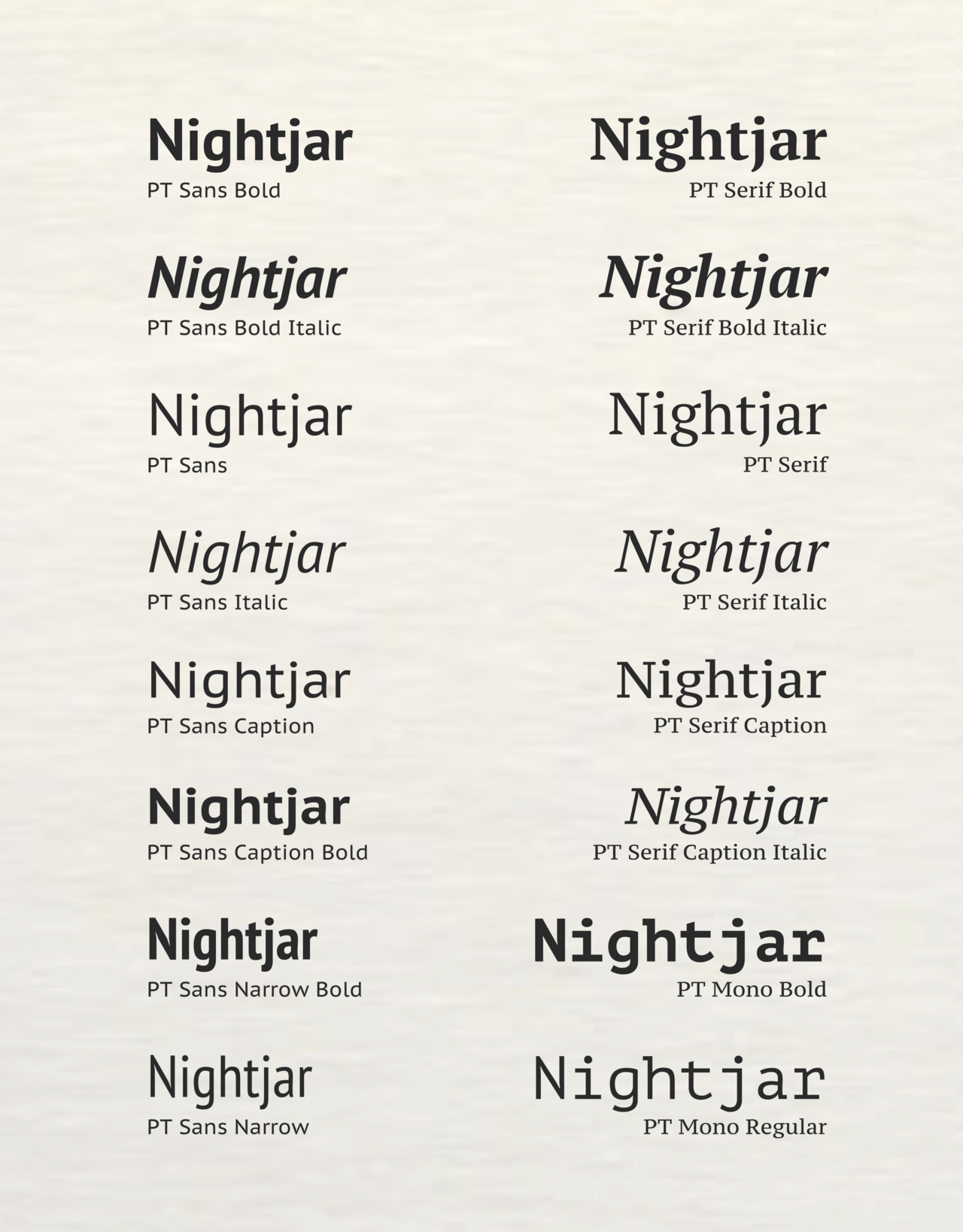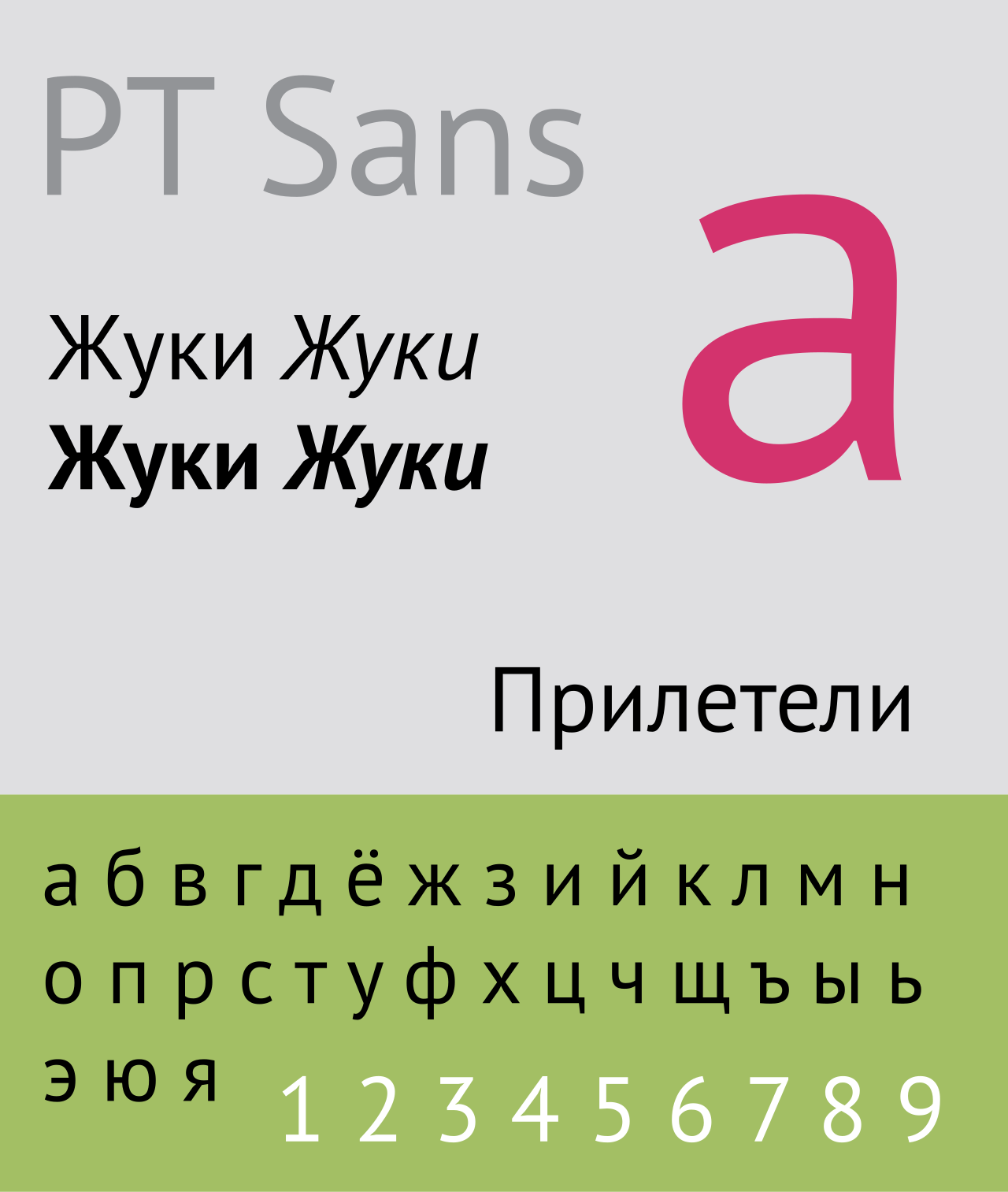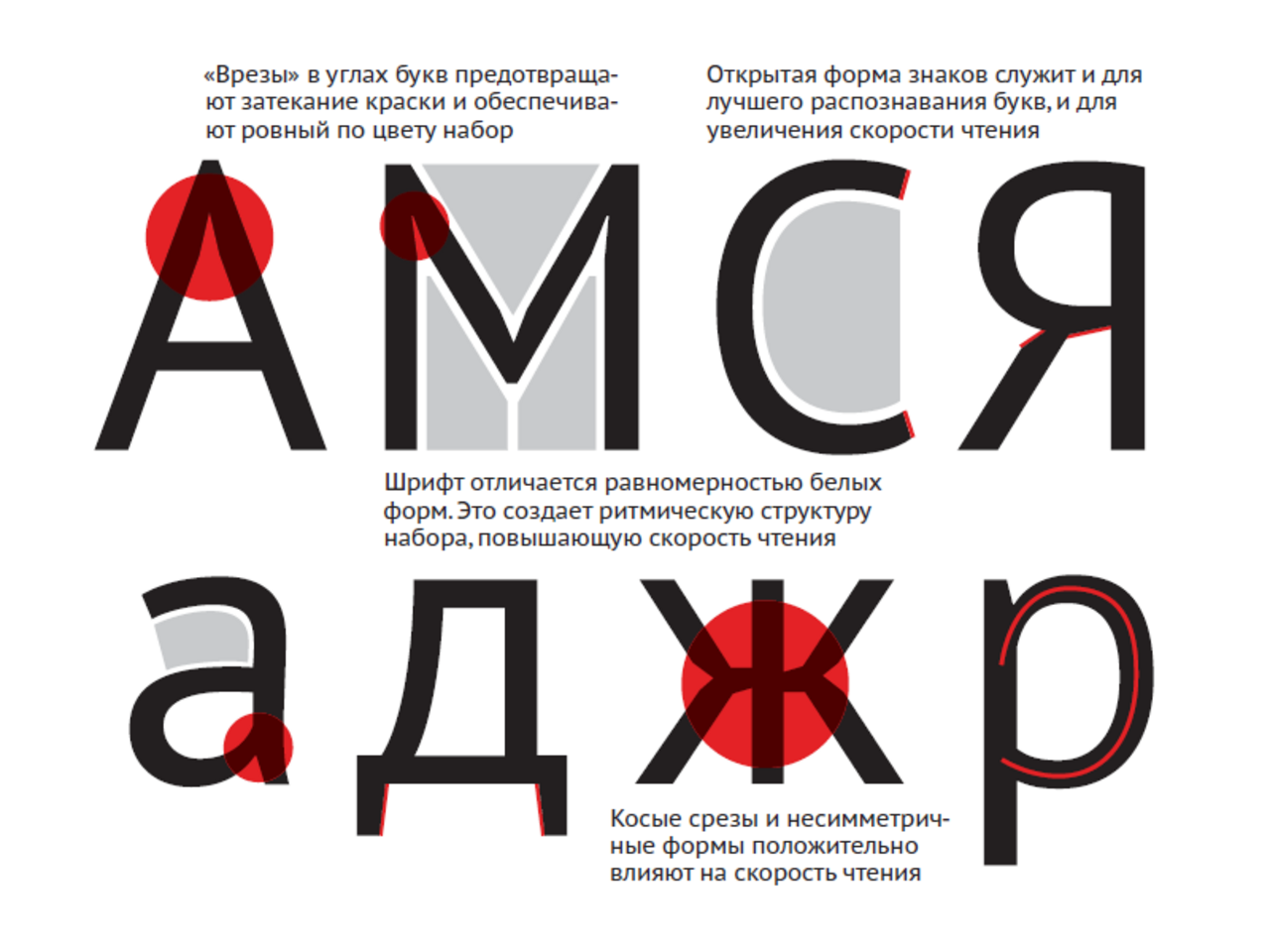
خطوط PT
| تصنيف | خط إنساني بلا رقيق انتقالي أحادي المسافة |
| المصمم(ون) | ألكسندرا كورولكوفا مع أولغا أومبيلوفا وفلاديمير يفيموف |
| بتكليف من | روزبشات |
| مسبك | النوع الفرعي |
| تاريخ الإنشاء | 2009 |
| تاريخ الإصدار | 13 يناير 2010 [1] |
خطوط Public Type أو PT هي عائلة من الخطوط المجانية والمفتوحة المصدر التي تم إصدارها منذ عام 2009 فصاعدًا، وتضم PT Sans و PT Serif و PT Mono . وقد تم تكليف وكالة التصميم ParaType بواسطة Rospechat ، وهي إدارة تابعة لوزارة الاتصالات الروسية ، بتصميم هذه الخطوط للاحتفال بالذكرى السنوية الـ 300 لإصلاح الإملاء الذي قام به بطرس الأكبر وإنشاء عائلة خطوط تدعم جميع الاختلافات المختلفة للنص السيريلي المستخدم من قبل اللغات الأقلية في روسيا ، بالإضافة إلى الأبجدية اللاتينية . [1] [2]
تم تصميم هذه العائلة في الأساس بواسطة ألكسندرا كورولكوفا ، وتتضمن تصميمات بدون تذييلات وتذييلات ، وكلاهما مع أنماط تعليق للنصوص المطبوعة بحروف صغيرة، وخط أحادي المسافة للاستخدام في البرمجة. وهي متوفرة بموجب ترخيص SIL Open Font باللغة الإنجليزية ؛ تم إصدار الخط الأصلي، PT Sans ، أيضًا بموجب ترخيص الخطوط المجاني الخاص بشركة ParaType، والخط العادي والغامق مع الخط المائل مجاني في Google. [3] يتم بيع أنماط إضافية، مثل الموسع والمكثف والغامق للغاية، من ParaType باسم PT Sans Pro وPT Serif Pro. [4] [5]
سمات
تتضمن الخطوط حروفًا لاتينية وسيريلية وتغطي جميع اللغات الأقلوية تقريبًا في الاتحاد الروسي. تم تضمين رمز الروبل المائل Р (قبل أن يصبح رسميًا في ديسمبر 2013) في نقاط الرمز U+20B9…U+20CF.
في أكثر إصدارات المصادر المفتوحة شيوعًا، يتميز PT Sans وPT Serif بتصميمات عادية ومائلة وغامقة ومائلة غامقة. كما يتضمنان نمط تسمية توضيحية : وهو إصدار أوسع من الخط مع ارتفاع x أكبر (أحرف صغيرة أطول)، مصمم لسهولة القراءة بأحجام الخطوط الصغيرة وعلى اللافتات الخارجية. يتضمن PT Sans أيضًا إصدارًا مكثفًا بالخط العادي والغامق بدون مائل. في أنماط التسمية التوضيحية، يحتوي PT Serif على نمط تسمية توضيحية مائلة بينما يحتوي PT Sans على إصدار غامق. يتضمن PT Mono أنماطًا عادية وغامقة.
تتضمن الإصدارات التجارية لخط PT Sans أوزانًا إضافية خفيفة وشبه غامقة وغامقة للغاية وسوداء، بأنماط عادية وضيقة ومكثفة ومكثفة للغاية. ويكتسب خط PT Serif 32 نمطًا إضافيًا، بعرض ضيق وممتد، وأوزان سوداء وغامقة للغاية وشبه غامقة. كما تضيف الإصدارات الاحترافية أشكال نصية وأحرفًا صغيرة .
خطوط PT Astra
في عام 2016، تم تطوير الخطين PT Astra Sans وPT Astra Serif للتوزيع مع نظام التشغيل الروسي Astra Linux . كلا الخطين متوافقان من حيث القياس مع Times New Roman . [10] [11] [12] في عام 2021، تم تطوير الخط PT Astra Fact للتوزيع مع نظام التشغيل Astra Linux. وهو متوافق من حيث القياس مع Verdana . [13]
ميزات PT Sans
ميزات PT Serif
الفرق بين الحروف السيريلية (أعلى) واللاتينية (أسفل) في PT Serif
الأوزان مفتوحة المصدر لسلسلة الخطوط PT.